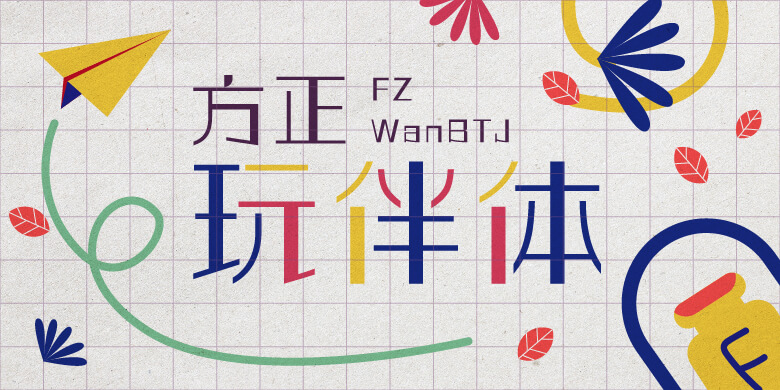
品牌:方正字库设计师:郭伟豪发行时间:2018字库编码:大陆简体(GB2312-80)、简繁扩展(GBK)分类:创意字体
玩伴体:创意源于郭炳权老师在网上看到的一个名为“Changing Partner Club”的外国俱乐部的标志字体,该俱乐部有酒和餐食,可以跳舞,但必须带一伴侣参与,而且可以自由交换伴侣来跳舞或聊天,“Changing Partner Club”的西文字体很特别,于是郭老师借鉴其风格设计了这款中文字体,并取名“玩伴体”。玩伴体的笔划透露出一种反叛的特质,给人一种新鲜的、与众不同的感受。它含8款粗细,适合面向年轻人的品牌,尤其是舞蹈用品、酒店、旅行社及品牌食品的广告宣传和包装设计。pop字体